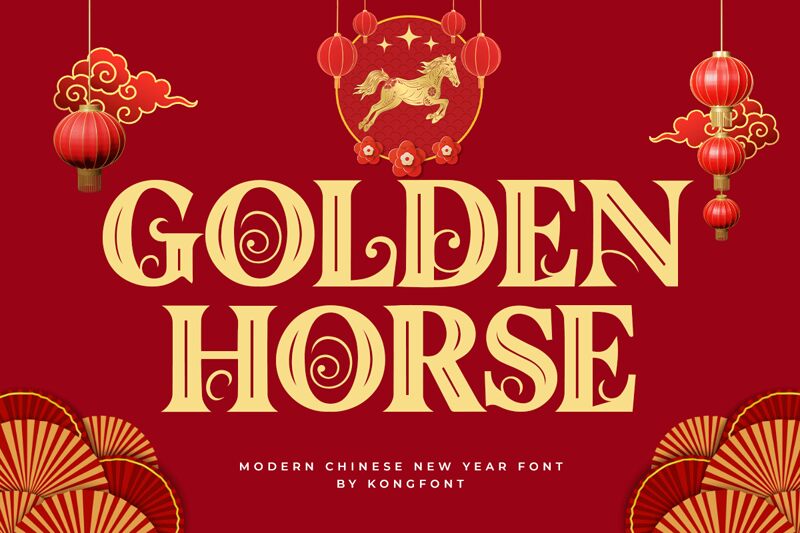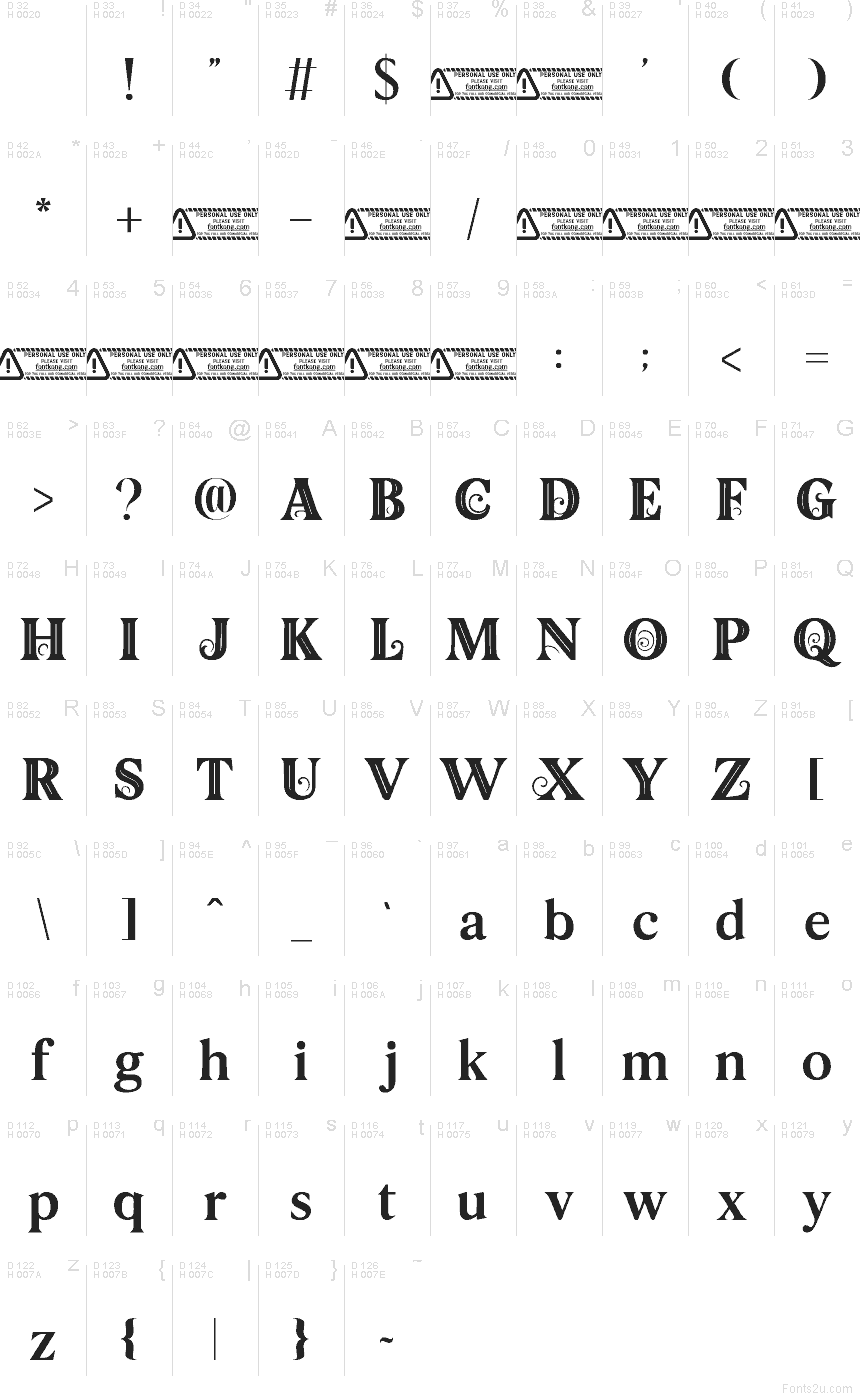
Golden Horse di Kong Font è un font display rétro gratuito con un fascino teatrale tipico dell'inizio del XX secolo. Le lettere combinano forme slanciate ad alto contrasto con morbide curve Art Nouveau, specialmente nelle maiuscole ornamentali, dando al font un'eleganza deliberatamente appariscente.
Funziona perfettamente per titoli di poster, packaging, branding di locali, copertine di libri e volantini di eventi dove si desidera un'atmosfera d'epoca senza risultare completamente antiquati. Essendo un font gratuito, è ideale anche per titoli brevi, bozze di loghi e iniziali in stile monogramma, poiché le sue curve ampie e le verticali nette conferiscono anche a poche lettere un carattere sufficiente a sostenere l'intero design.